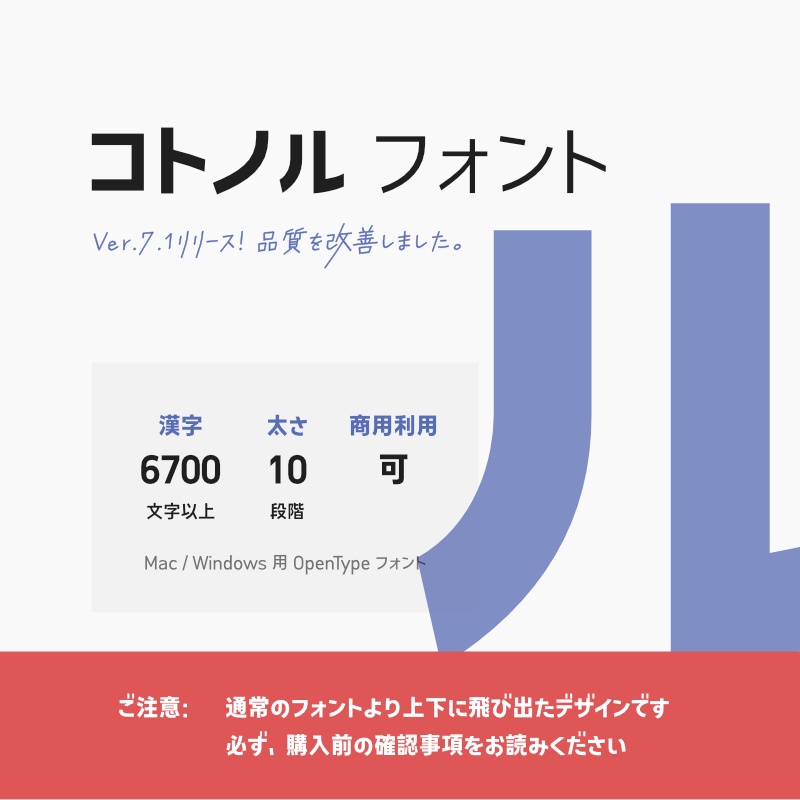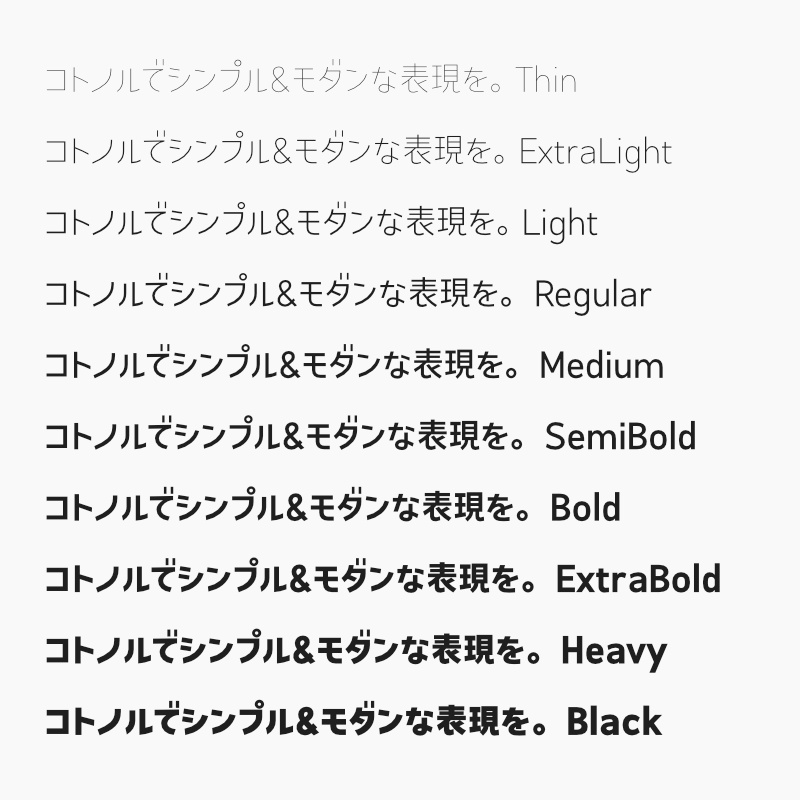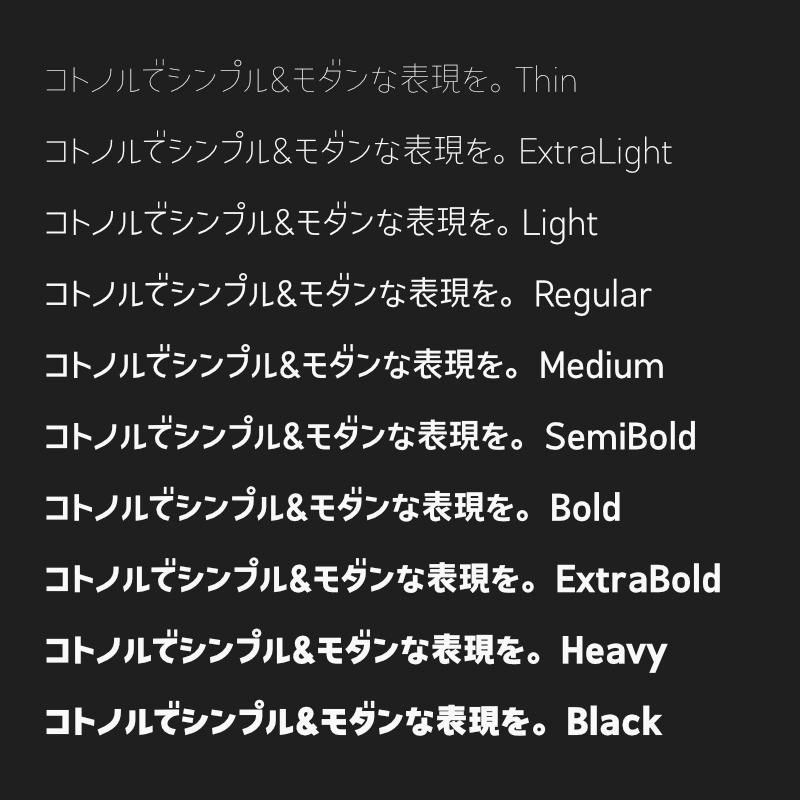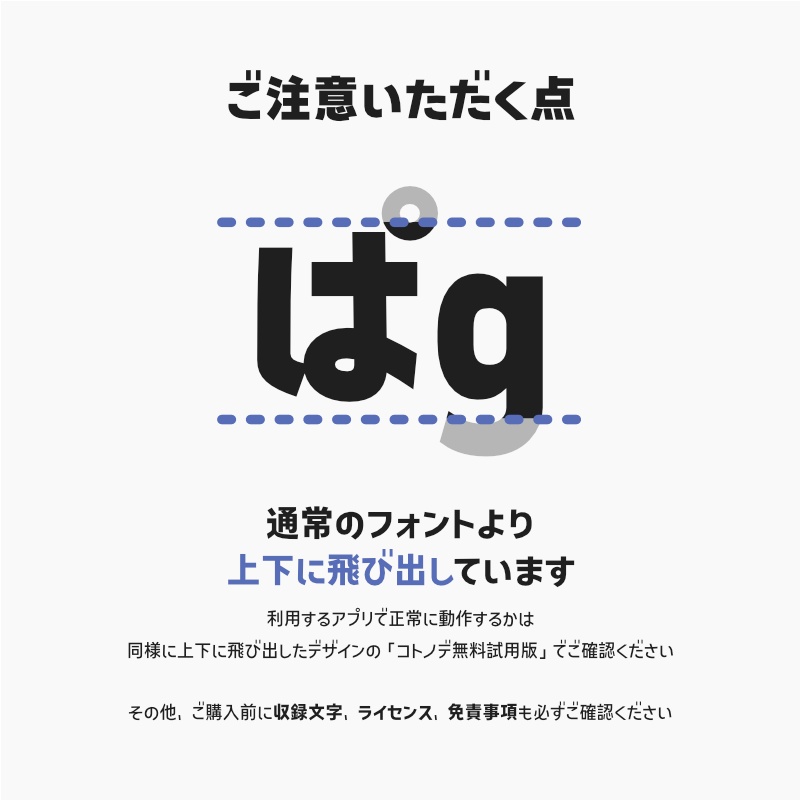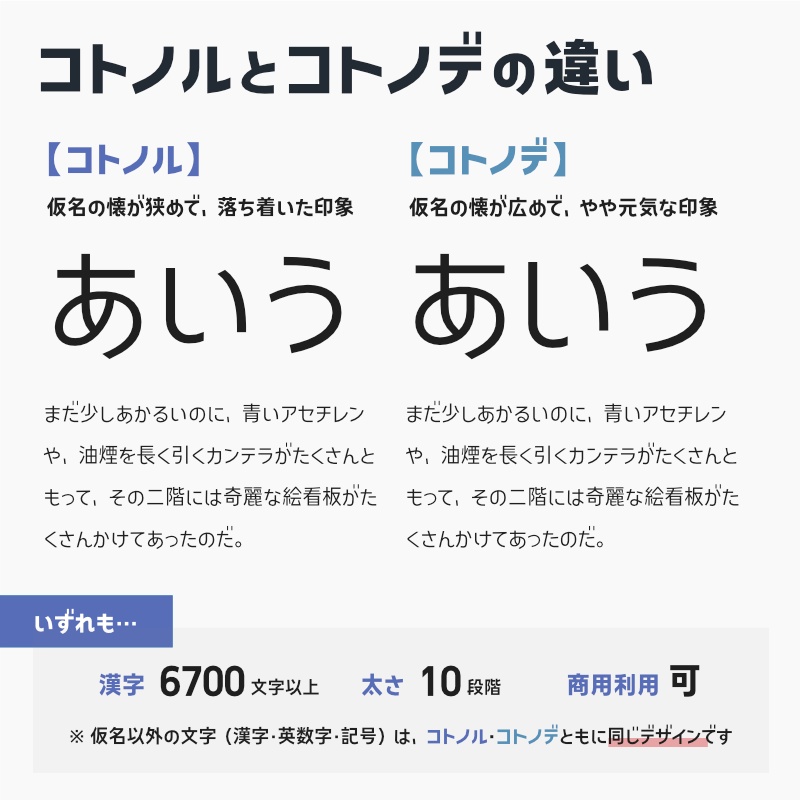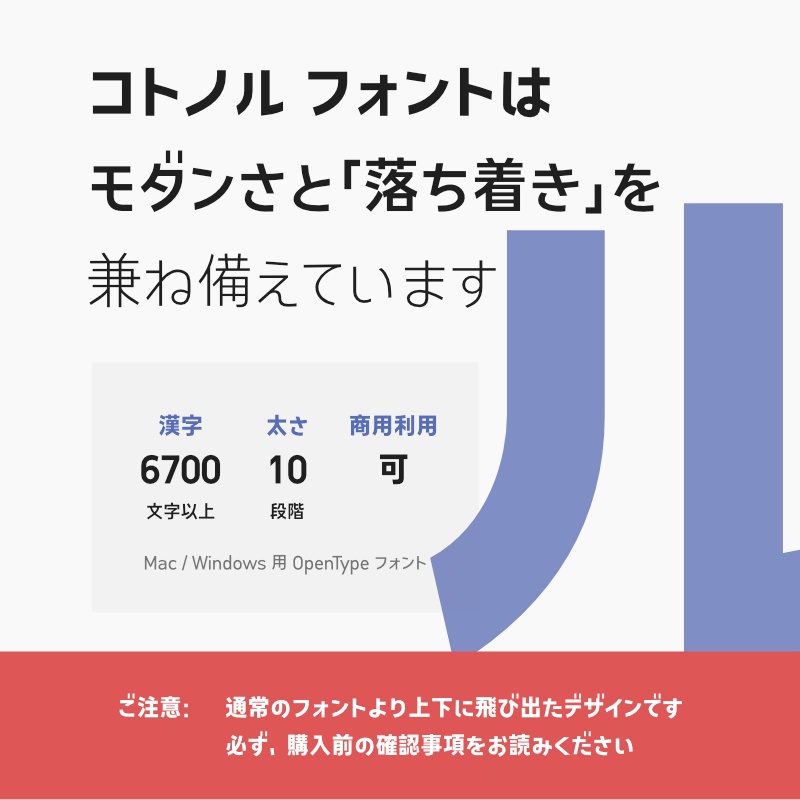
「コトノル」フォント(漢字あり) ~スタイリッシュでかっこいいゴシック体~
・通常のフォントよりも上下にはみ出たデザインです。ご利用のアプリによっては上下が見切れることがあります。ご購入前に確認したい場合は、同様に上下にはみ出たデザインの「コトノデ無料試用版(※)」をご活用ください。 ・漢字は6,700文字以上収録しており、常用漢字・JIS第一水準漢字・JIS第二水準漢字をカバーしています。収録文字は公式の紹介ページをご確認ください。 ・公式の紹介ページの利用規約・免責事項を必ず確認してください(商用利用可・再配布禁止)。 【公式の紹介ページ】 https://kotonohaworks.com/kotonoru.html (※コトノデ無料試用版) https://dkf.booth.pm/items/2727320(無料試用版に漢字は含まれていません。)